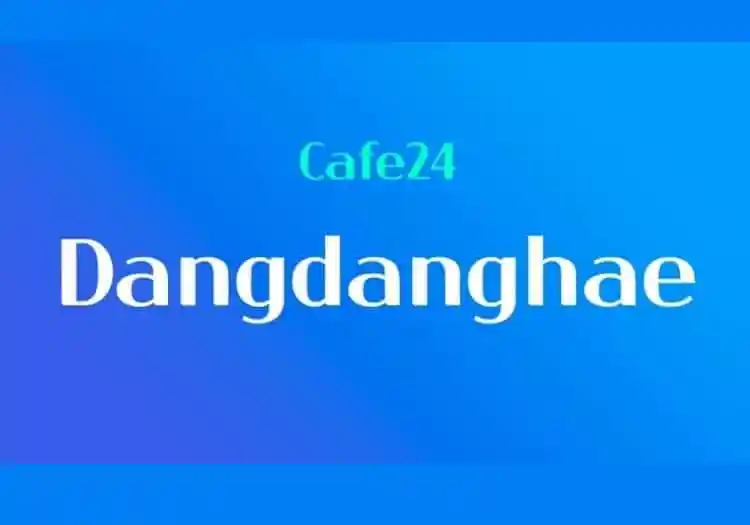
Dangdanghae Sans Serif Font – Download Grátis
A Dangdanghae Sans Serif é uma fonte moderna desenvolvida para transmitir um tom de voz estiloso inspirado na beleza e elegância dos tipos tipográficos de estilo sério atual. Essa fonte seria perfeitamente adequada para uma variedade de usos de exibição, como logotipos, painéis, subtítulos, citações e muito mais. Seu design moderno, mas ainda mantendo uma certa sofisticação, a torna uma opção ideal para marcas e projetos que buscam um visual clean e contemporâneo sem perder o brilho do estilo tradicional. Ela é perfeita tanto para aplicativos digitais quanto impressão em cartolina. Com Dangdanghae, você pode garantir uma experiência gráfica moderna e sofisticada, combinando elegância com simplicidade.